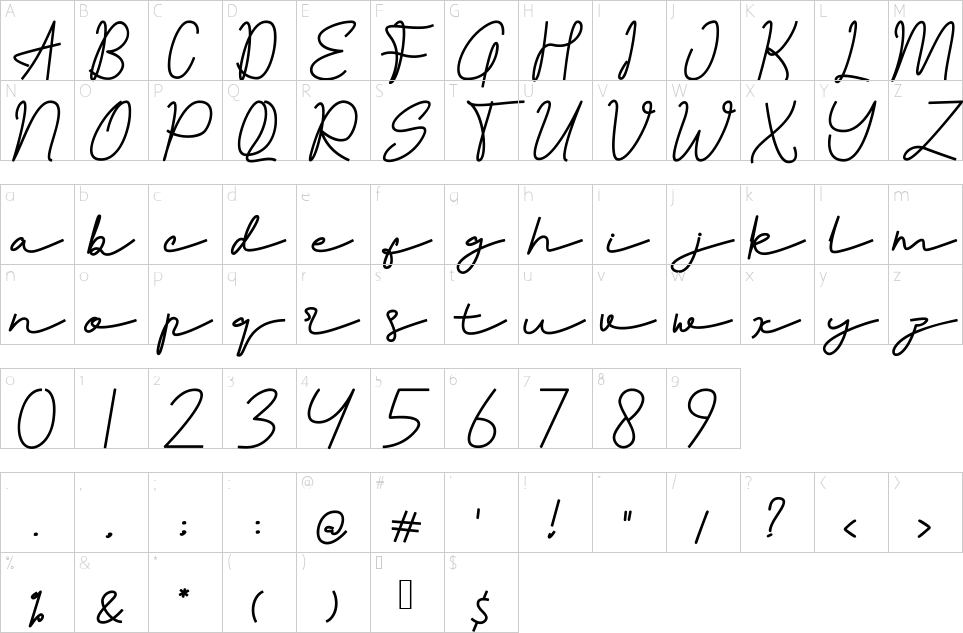
Peacelove é uma fonte elegante e versátil que adicionará um toque de paz e calma a qualquer projeto. Desenhada por Muhamad Ali Hasan, esta fonte é ideal para designers que buscam uma opção tranquila e agradável para textos em suas criações. Com sua aparência minimalista e harmoniosa, Peacelove é especialmente adequada para design gráfico, criação de websites e qualquer projeto que necessite de uma fonte confortável e harmônica. Com mais de 11.286 downloads, é claro que a comunidade de designers valoriza o desempenho desta fonte, que se destaca por sua facilidade de leitura e simplicidade. Seja você um designer profissional ou iniciante, você certamente vai apreciar o cuidado e a atenção ao detalhe que o desenvolvedor dedicou à criação de Peacelove. Com certeza, ela será uma escolha ótima para qualquer projeto que deseje um acabamento agradável e desejável.